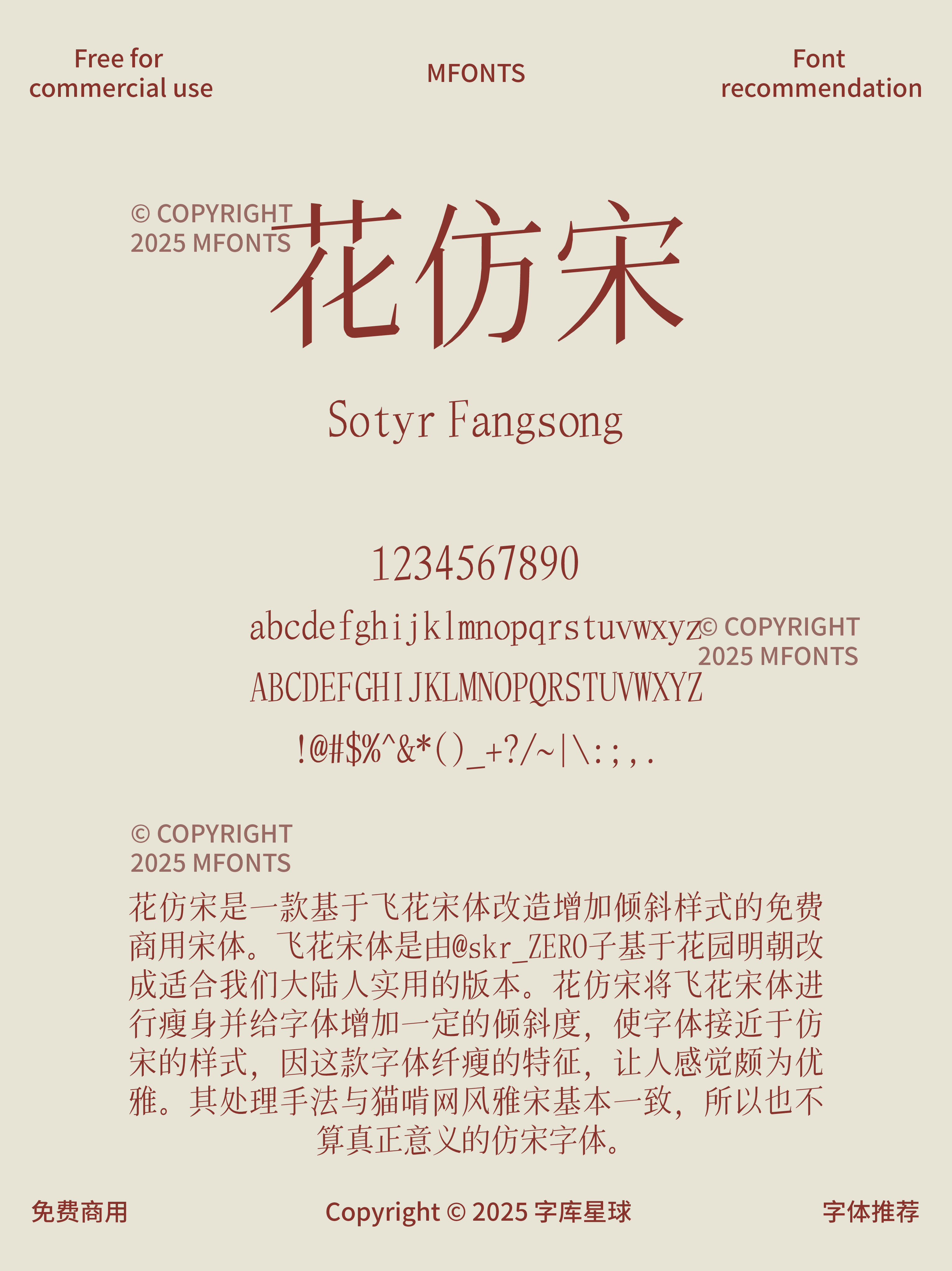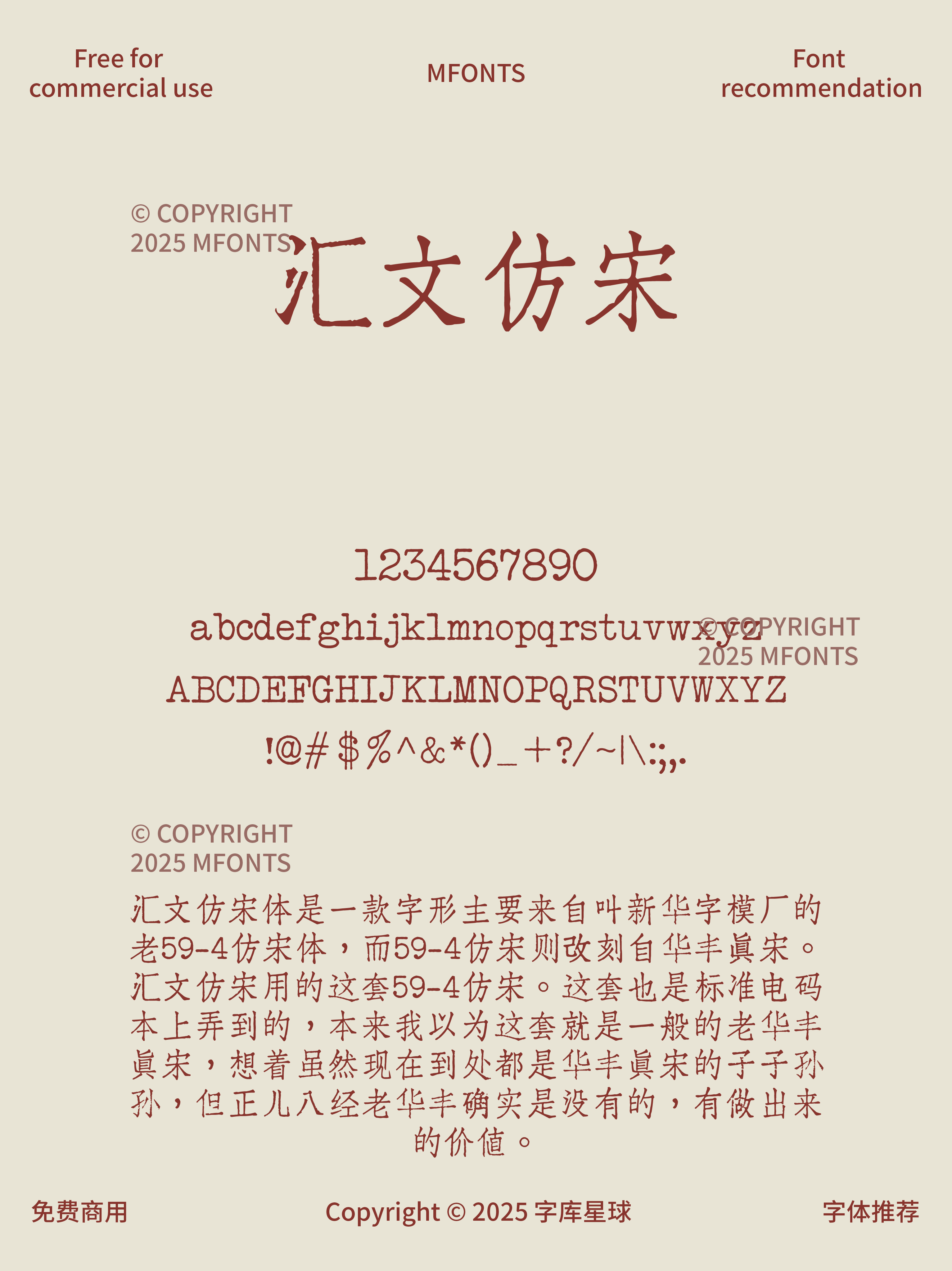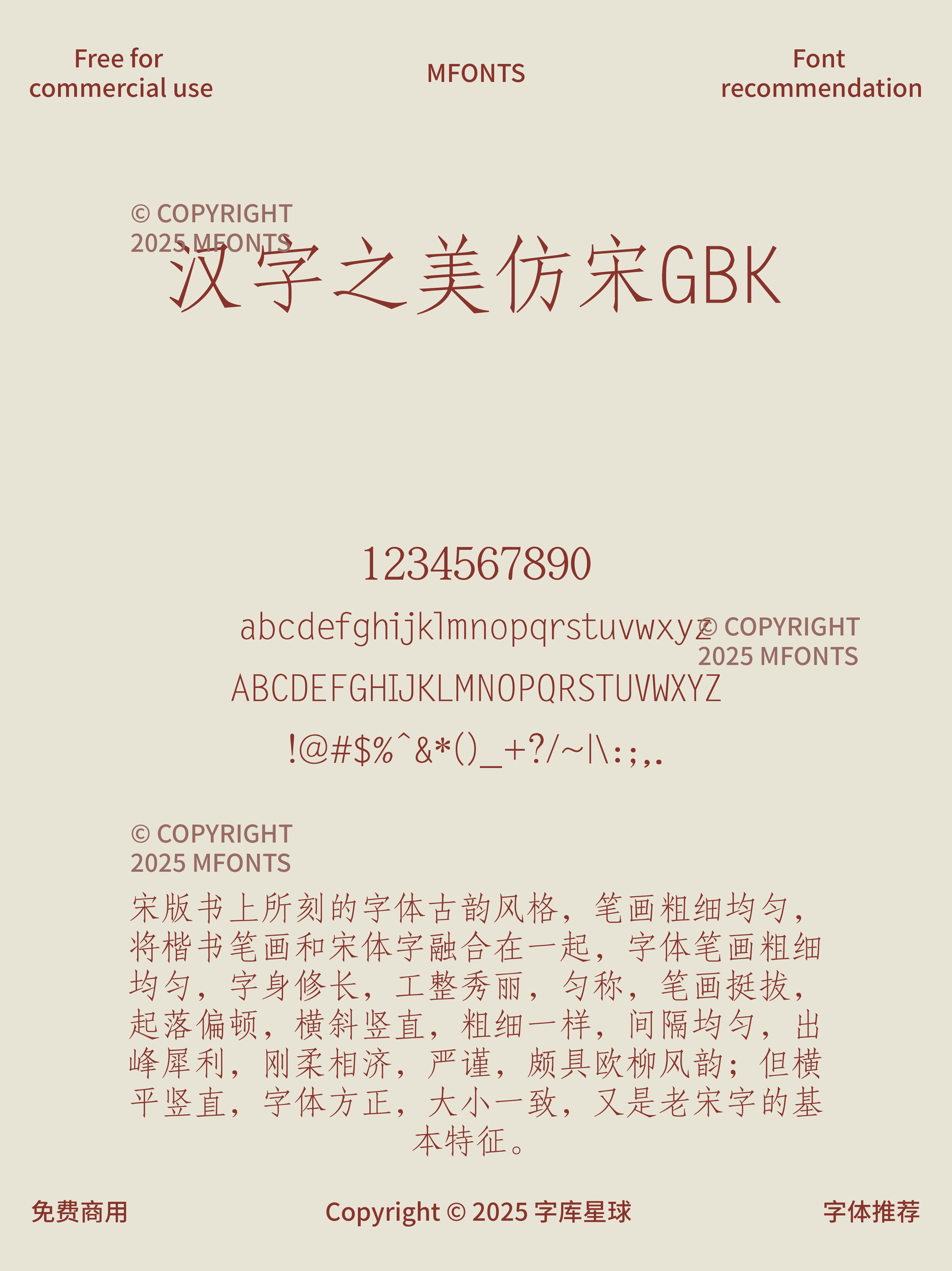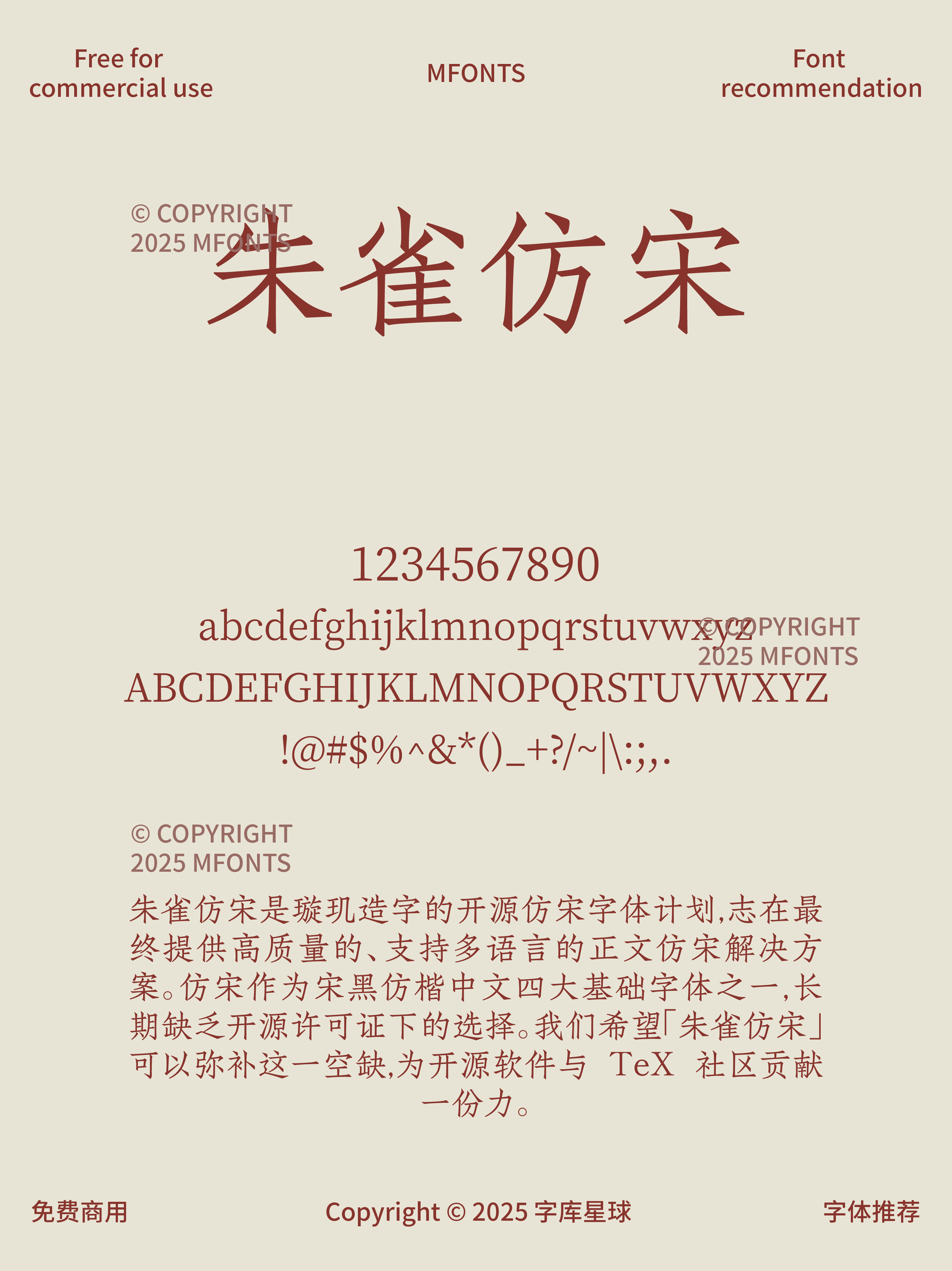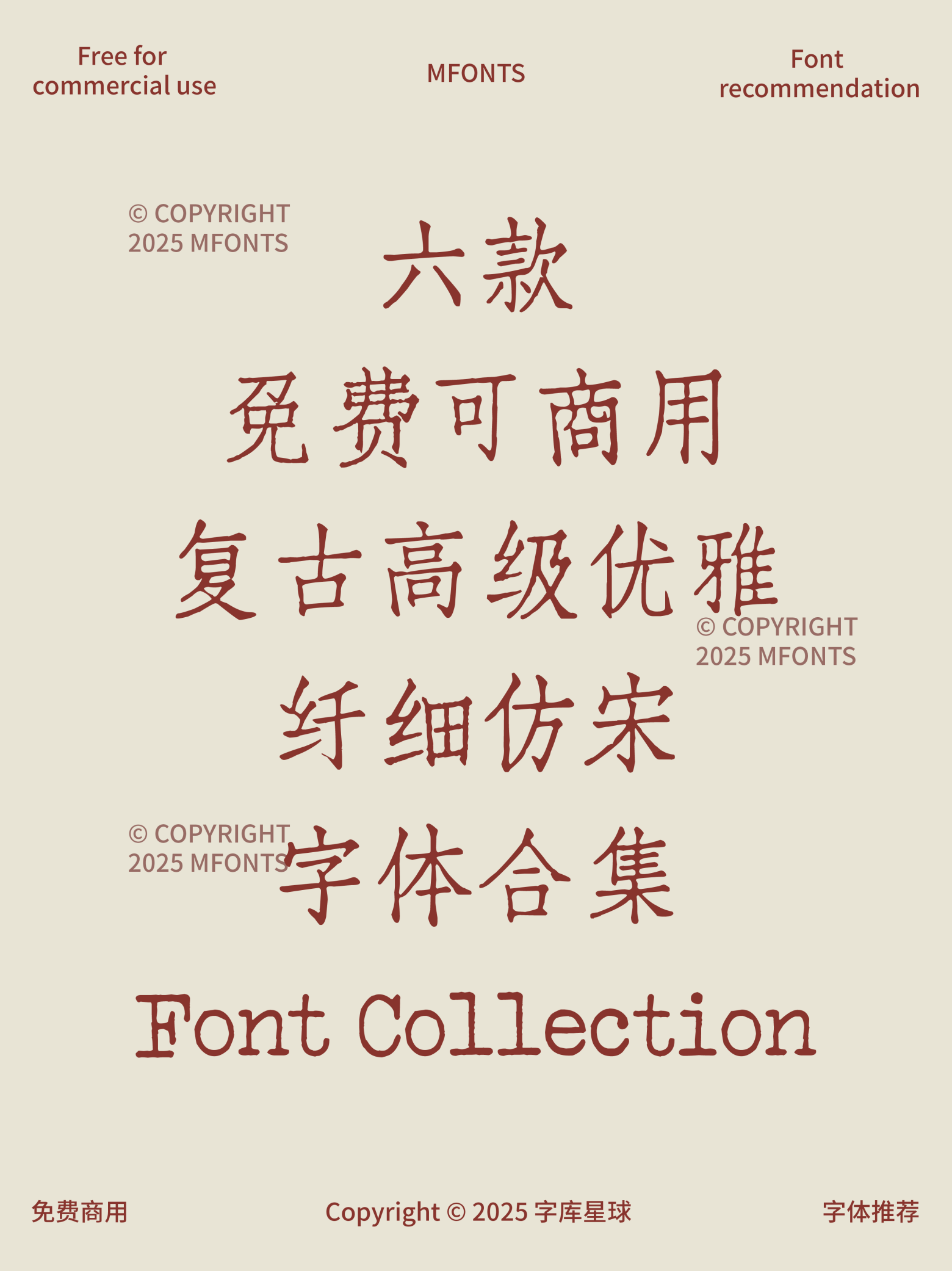
六款免费可商用复古高级优雅纤细仿宋字体
今天给大家分享 6 款超美的免费可商用复古高级优雅纤细仿宋字体,让你的设计瞬间提升格调!
仿宋体​​是中国近现代印刷字体中的一种重要类型,兼具书法艺术与工业实用性的特点。仿宋体笔画粗细均匀,横画略向右上倾斜(约3度),起笔与收笔处带有楷书顿挫感,整体刚柔并济,兼具楷书的灵动与宋体的规整。
因其笔画清晰、结构严谨,被广泛用于技术图纸、工程制图及公文排版,兼具美观与功能性。早期用于古籍整理,后成为报刊、书籍正文常用字体。现主要在广告、品牌标识、数字化界面设计中广泛应用,尤其适合传达文化底蕴与经典感。